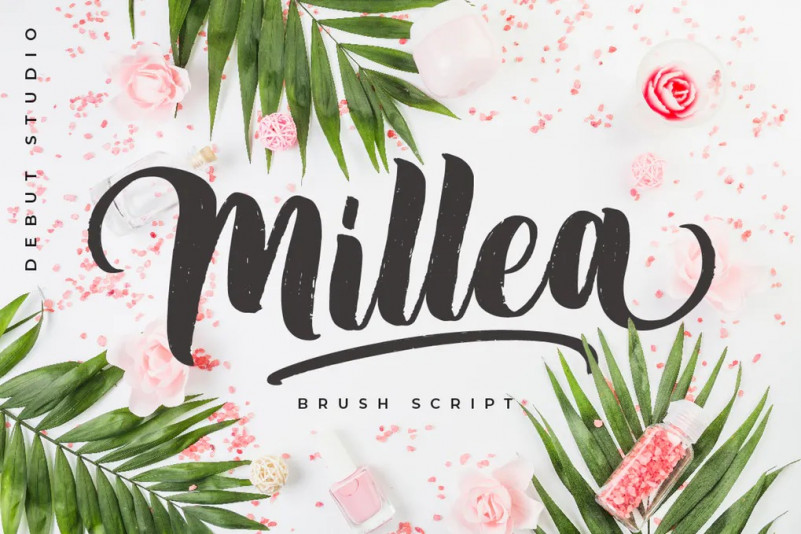
Millea Font
Millea Brush Script est une belle police de pinceau, conçue pour combiner parfaitement et vous permettre de créer un superbe lettrage à la main rapidement et facilement. Idéal pour les Logos, citations manuscrites, emballage de produits, en-tête, affiche, marchandise, médias sociaux et cartes de vœux.